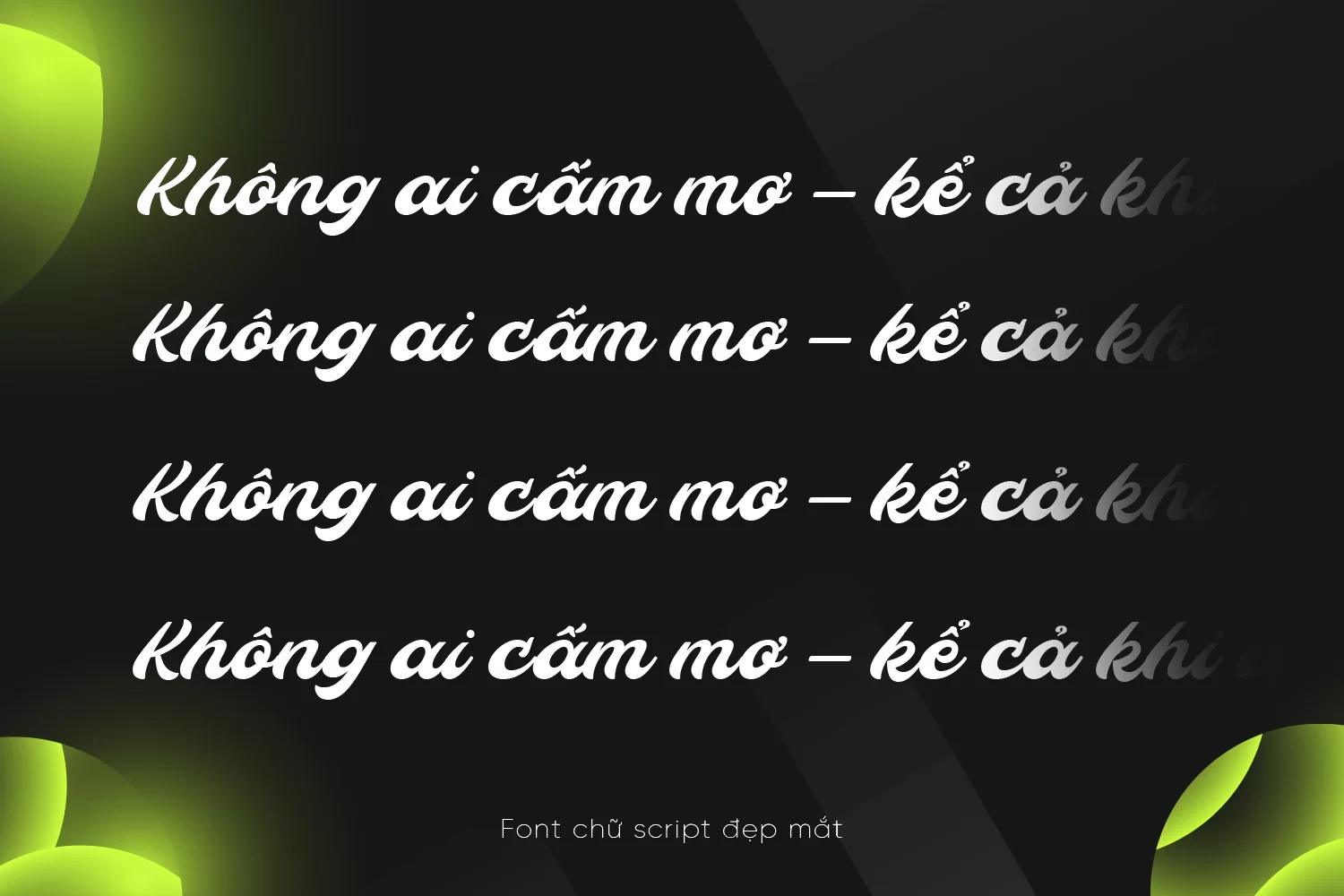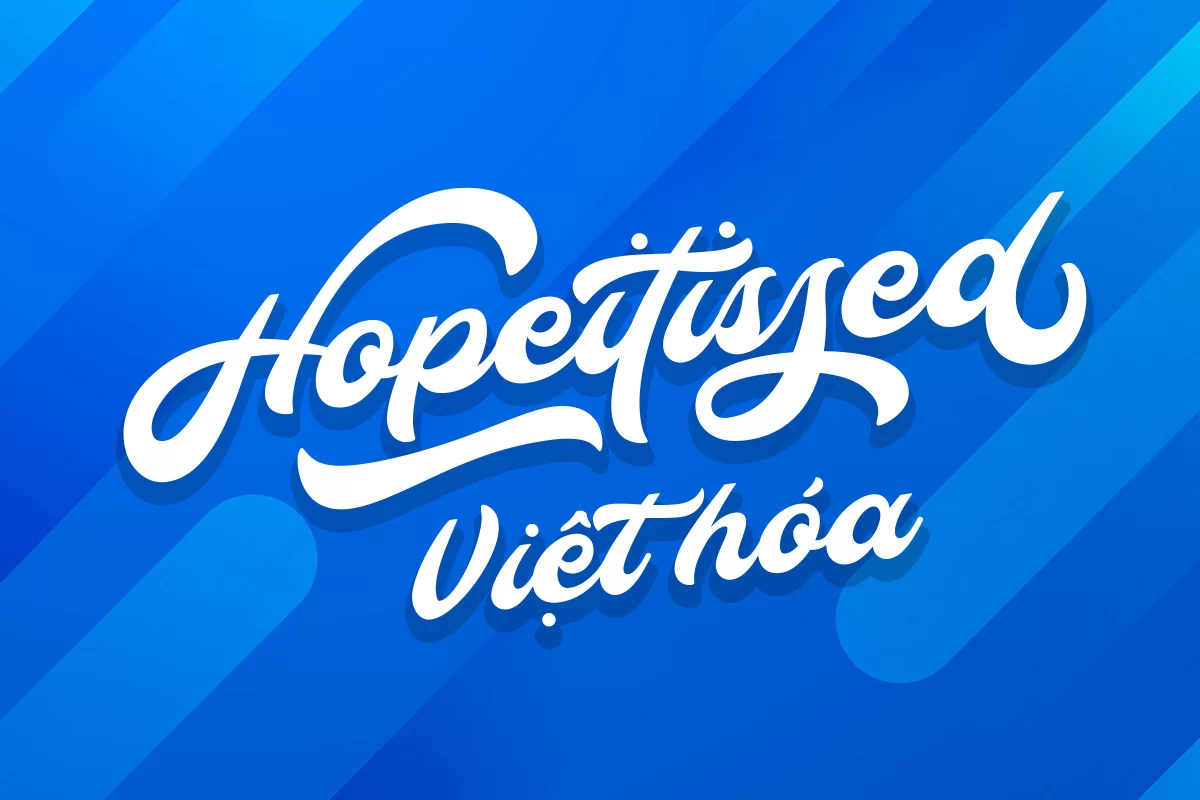
Font Hopeitissed Việt Hóa - Kiểu chữ Script phong cách cổ điển
Hopeitissed là một phông chữ Script tuyệt đẹp tuyệt vời được chế tác theo phong cách retro cổ điển. Gợi nhớ đến các thương hiệu của năm qua, font chữ này mang đến cho các thiết kế của bạn một cảm giác hoài cổ nhưng vẫn hiện đại.
*Font rất nhiều Glyphis nên mọi người sử dụng được thuận tiện